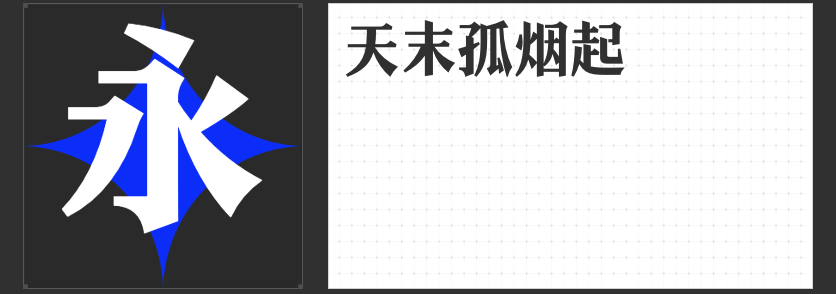
怀旧风情,设计首选:四款经典字体推荐
在设计中,字体不仅是文字的表达,更是情感的传递者。怀旧风格的设计总能唤起人们内心深处的共鸣,而选择恰当的字体则是营造这种氛围的关键。今天,我们就来推荐四款专为设计而生的怀旧字体,它们不仅承载着历史的记忆,更能在现代设计中焕发新的生命力。
一、字圈也字山海明朝
这款字体巧妙地将宋体的衬角装饰与黑体的硬朗架构相结合,创造出既大气又富有趣味性的视觉效果。在保留黑体转折特点的同时,适当减少了宋体的柔美书写特征,使得字圈也字山海明朝体在标题和正文排版中都能游刃有余,既醒目易读又不失艺术感。
二、励字大标宋简繁
励字大标宋简繁以其横轻竖重、字形端正的特点,展现出老宋体与黑体的完美结合。笔画粗细变化有致,点、撇、捺等笔画尖端的设计,更是增添了字体的刚劲有力。这款字体端庄清秀,无论是用于标题还是正文,都能彰显出独特的韵味和气质。
三、字圈也字幼稚黑体
字圈也字幼稚黑体以其特有的喇叭口形状装饰,成为极具时代印记的一款字体。这款字体在保持黑体规矩与方正的基础上,通过笔画端口的装饰,赋予了字体端庄而不失活泼的气质。它仿佛带着我们穿越回那个铅字印刷的时代,感受那份独特的工艺美感。
四、云书法三行魏碑体
云书法三行魏碑体以其工整的楷书字形和古风韵味,成为设计中的一大亮点。笔划严谨而朴厚灵动,风格朴拙险峻又舒畅流丽。这款字体适用于多种设计场景,无论是标题还是正文,都能展现出其独特的艺术魅力和历史底蕴。
这四款字体各具特色,共同构成了怀旧风格设计中的一道亮丽风景线。它们不仅承载着历史的记忆,更能在现代设计中为我们带来无限的灵感和惊喜。选择它们,为你的设计作品增添一份独特的韵味吧!